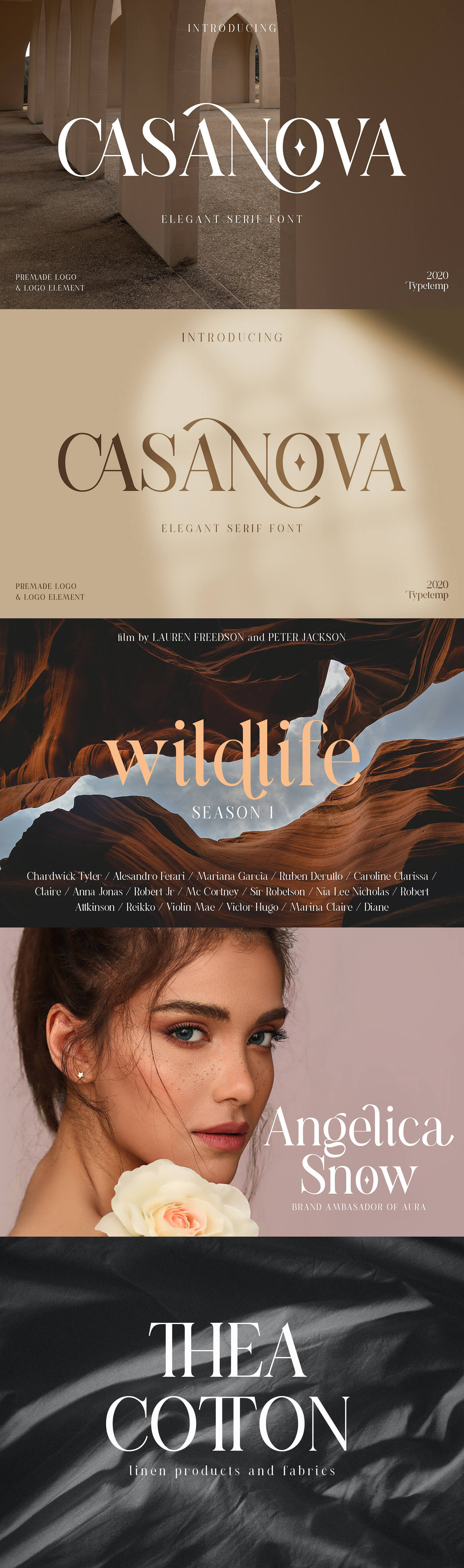
А почему у меня этот шрифт как отдельные буквы, а не как тут красиво соедененные?
Анна Гор, потому что у него не работают лигатуры. Возможно они доступны только в платной полной версии.